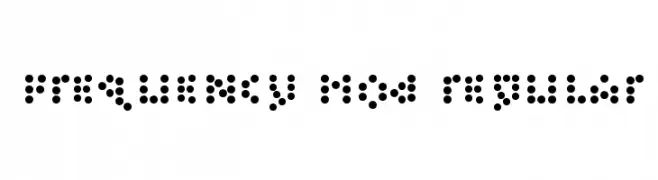
A modern, dot-based font with a digital and futuristic style.
近期热门包括 Frequency Mod Regular, Glimmer, Menga, Numan and 486 Regular 它们在清晰度与个性之间取得平衡,适用于科技品牌、编辑排版与社媒视觉。